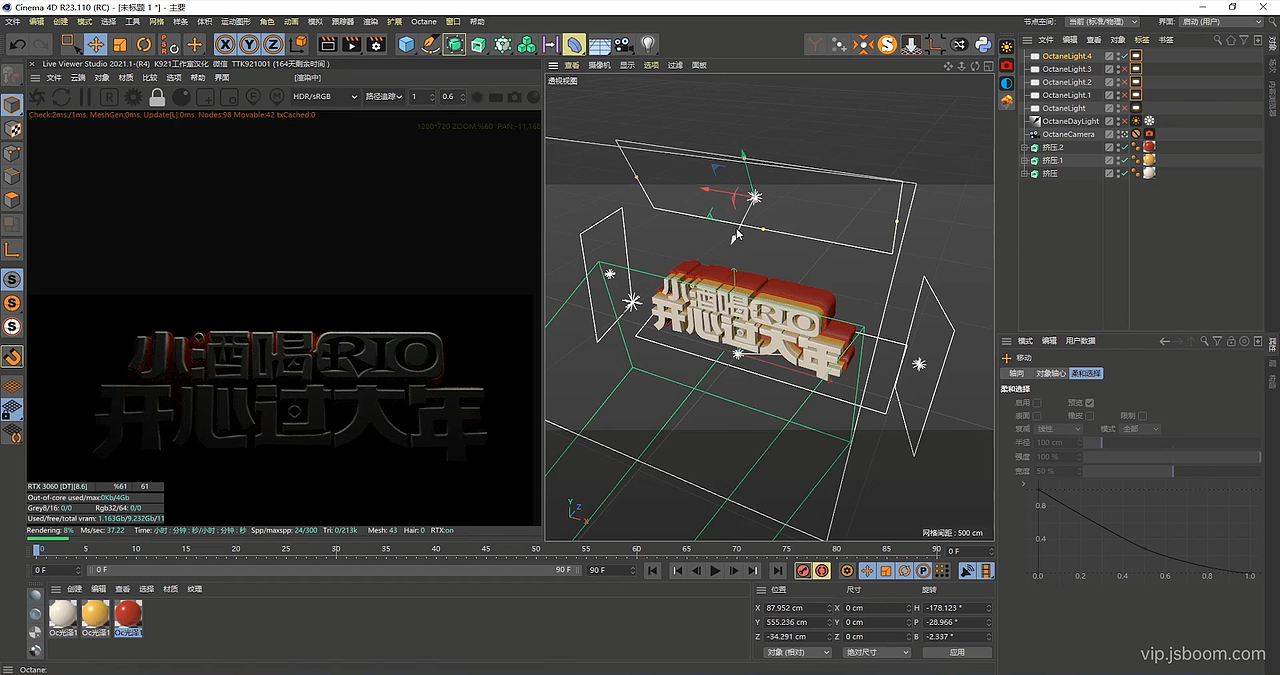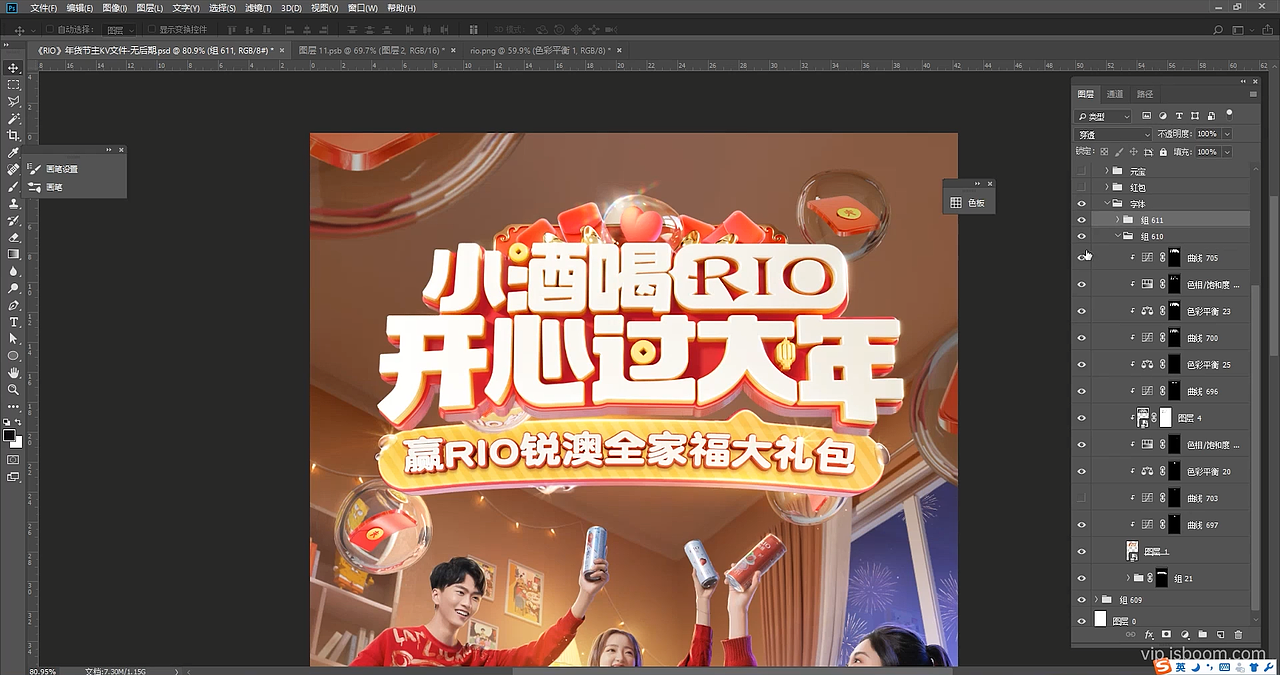
如何快速搞定电商大促风三维字体?
随着C4D的流行,用三维做字体的需求越来越多
特别是一些大促风格字体的使用频次更高~
那么,这类高频使用的字体效果,用三维该怎么做呢?
诶~ 这不,教程来了~😁
👉三维字体设计全流程讲解
👉字体层次表现与空间关系实操演示
👉字体饱满度打光技巧分享
👉PS后期润色原则讲解与实操演练